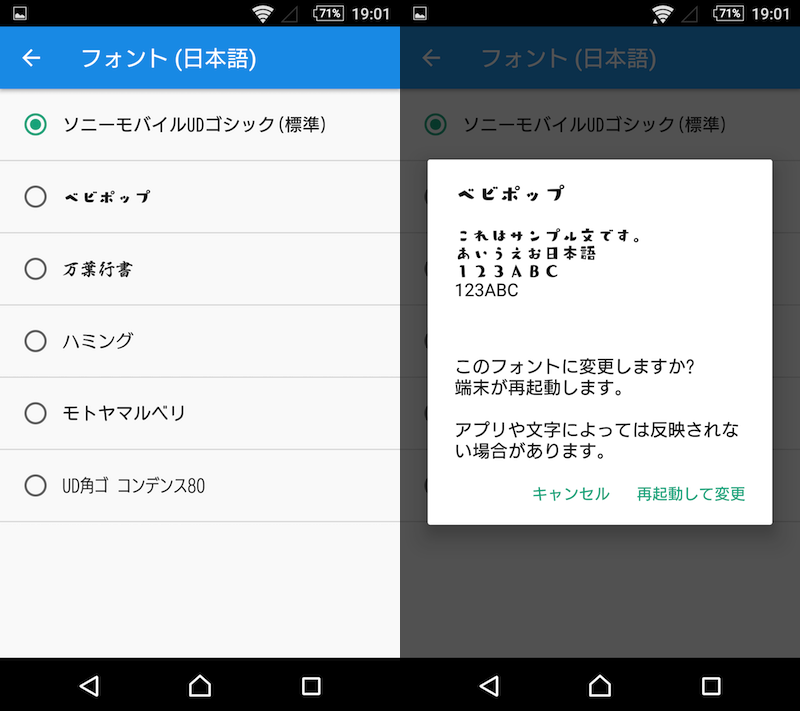
ギャラクシー フォント
ただ、標準フォントしかなったんですよぉ。 >>ぱぐこさんは、ポップ、丸ゴシックなどを使われてたのかな? そう言うのではなくてギャラクシーのフォントは本当に可愛かったんです。 手書き文字のような >望見者さん.
ギャラクシー フォント. Galaxy S7 edgeでは標準でフォントの変更が可能 Androidのフォント変更というとroot化してファイルを入れ替えて・・・というのを当たり前に行っていた時期もありますが、Galaxy系の端末は以前から標準でフォントの変更が可能です。. うずらフォント /サンプル /縦書きサンプル オリジナルの手書きフォントです。 あずきフォントよりも少し太くて少し丸い. ギャラクシー フォント ダウンロード ⭐ 谷村新司 階 無料 ダウンロード 高港基資 マサイ 無料 ダウンロード Office 07 ダウンロード 方法 快活クラブ 動画 ダウンロード スマホ かわいい犬 ダウンロード ダウンロード ヘルパー 最新 版 Linux rpm ダウンロード コマンド 🔥.
A 設定で文字の表示サイズを変更することができます 下記の手順で設定を変更すると、GALAXY Tab 77 Plusで表示される文字の表示サイズを5段階から選ぶことができます。すべてのアプリで変更できるわけではありませんが、Gmailなどのアプリでは文字の表示サイズが変わります。. 解決済み 前機S7edgeは標準でいくつかフォントがあって、添付の画像のポップというフォントに変更して使ってました。 日本語も韓国語も可愛くて気に入ってたんですが、S10ではなくなっちゃったんですね~🥺 自分でフォントを追加できるようだけど有料ばかりだし. PostScript プリンターと非 PostScript プリンターで使用するための Adobe Acrobat Pro での PDF 印刷の詳細設定(PostScript オプション、出力オプション、ハーフトーンスクリーン線数、膜面と画像のネガとポジ、トンボと裁ち落とし、カラーマネジメントオプション)について説明しています。.
Galaxy S7 edgeでは標準でフォントの変更が可能 Androidのフォント変更というとroot化してファイルを入れ替えて・・・というのを当たり前に行っていた時期もありますが、Galaxy系の端末は以前から標準でフォントの変更が可能です。. CSS初心者向けに、fontfamilyを使ってフォントを指定する方法を解説する記事です。 CSSの基礎がわからない場合は、CSSの書き方の記事を先にお読みください。 本記事は、TechAcademyのWebデザインオンライン講座のCSSのカリキュラムをもとに執筆しています。 なお、今回の記事の内容は動画でもご覧. Galaxy SやGalaxy S IIなど、フォント変更機能が標準搭載されているGalaxyスマートフォン向けのroot化不要のフォント変更アプリ「Font for Galaxy SP」が最近のアップデートで日本語フォントを提供するようになりました。.
Galaxyスマートフォンには、フォントを変更する仕組みがあります。 下は私が愛用しているグローバル版Galaxy S9。最初から4つのフォントがインストールされており、ユーザは好きなものに変更することができます。 下は標準フォント。ゴシックで、とても見やすいです。. Galaxy SやGalaxy S IIなど、フォント変更機能が標準搭載されているGalaxyスマートフォン向けのroot化不要のフォント変更アプリ「Font for Galaxy SP」が最近のアップデートで日本語フォントを提供するようになりました。. Galaxy S・Galaxy Sを使いこなそう!どうも、スマホ買っちゃう系ガジェットライターちえほんです。TwitterとYouTubeもやってます。 Galaxy S/Sを快適に使うためおすすめの基本設定から便利機能をじっくりお伝えしていきます。.